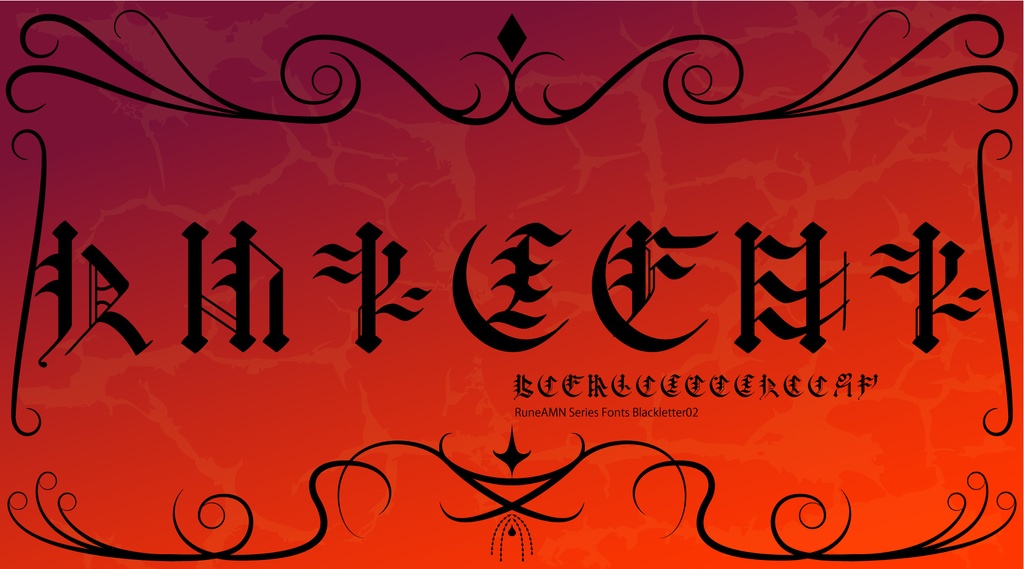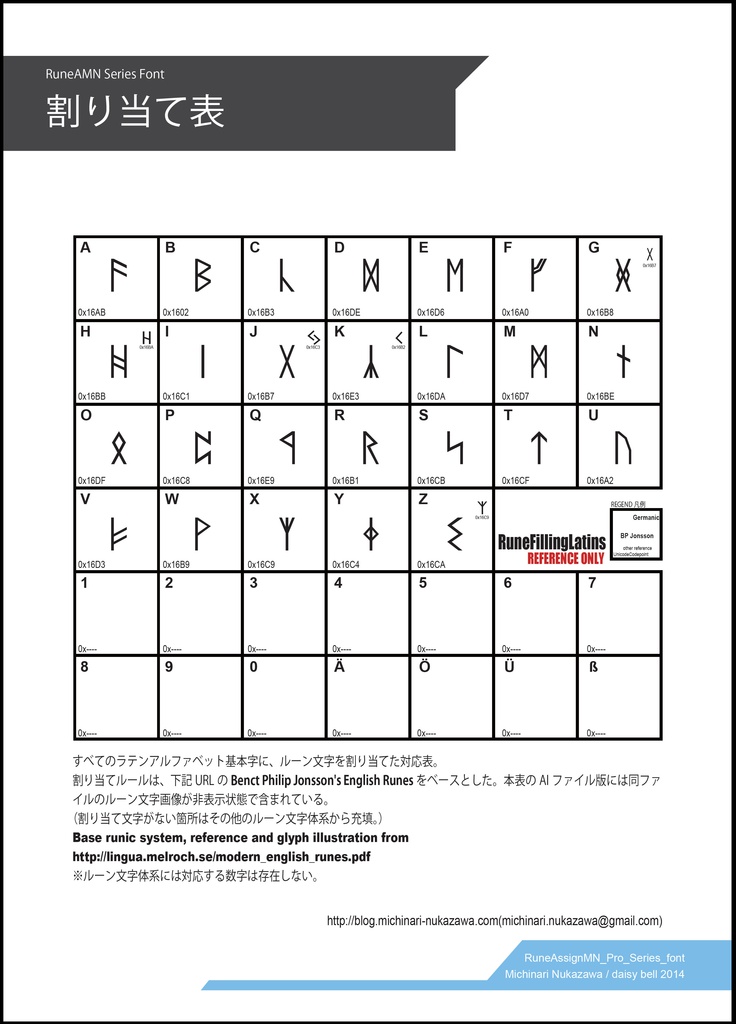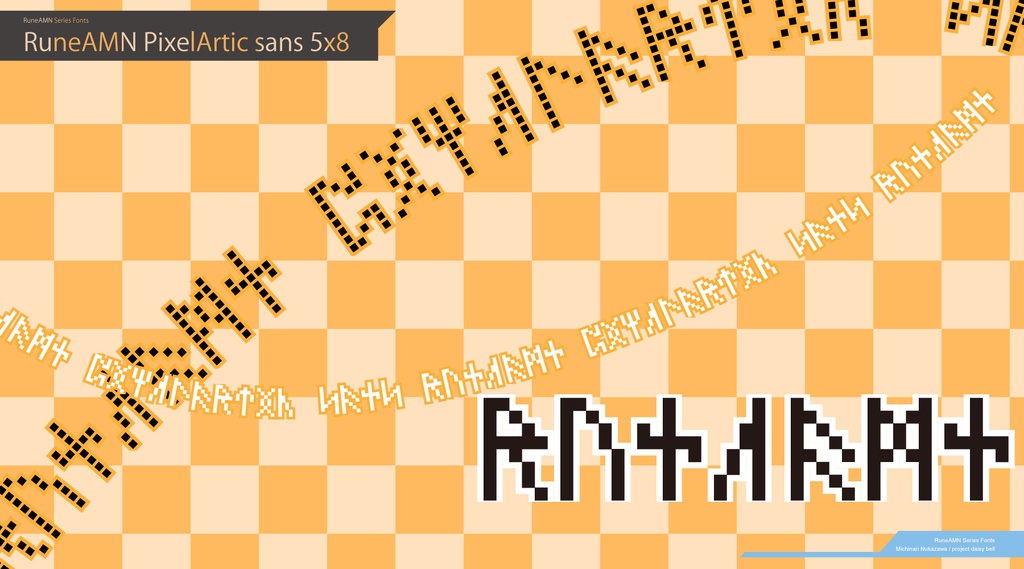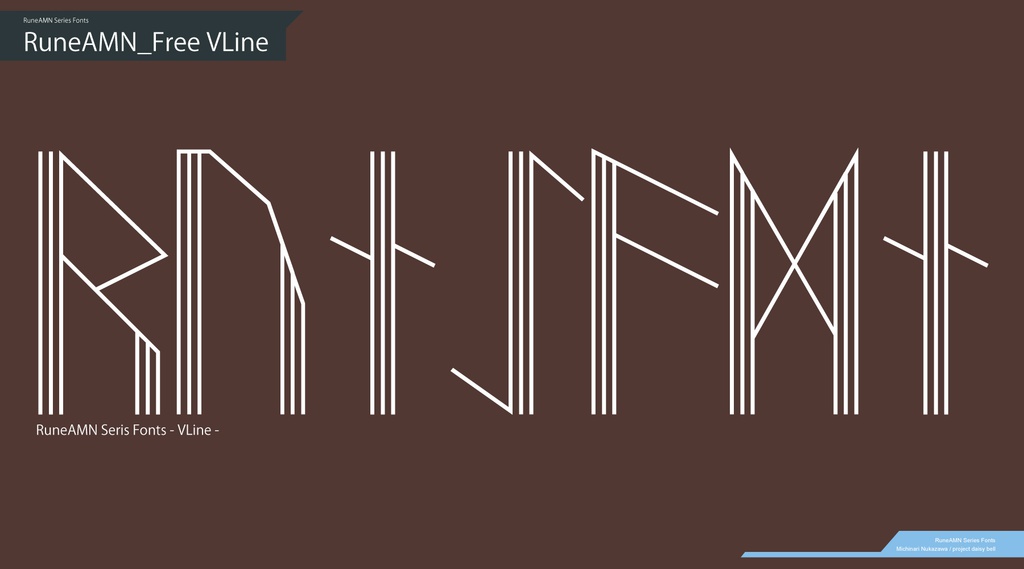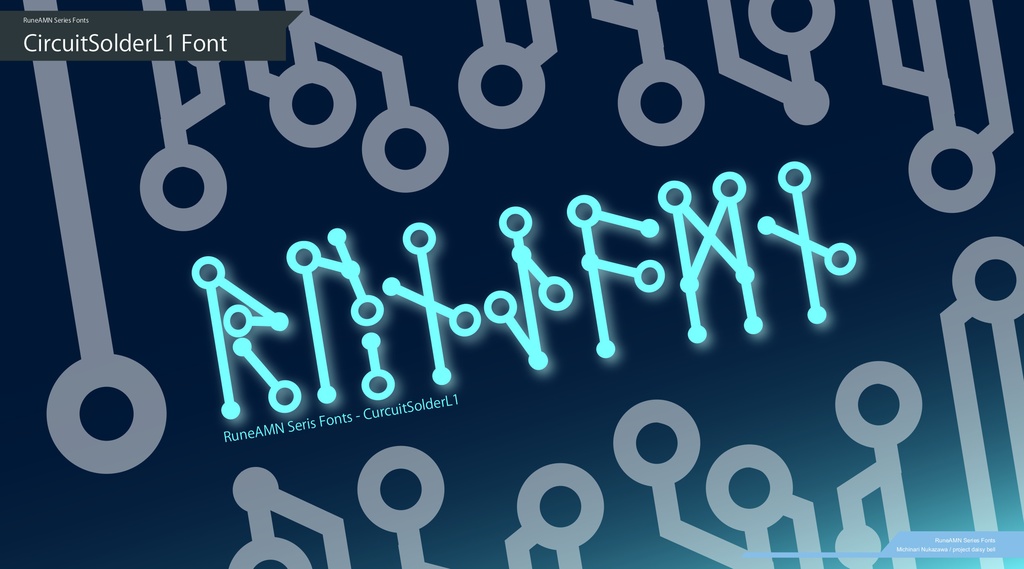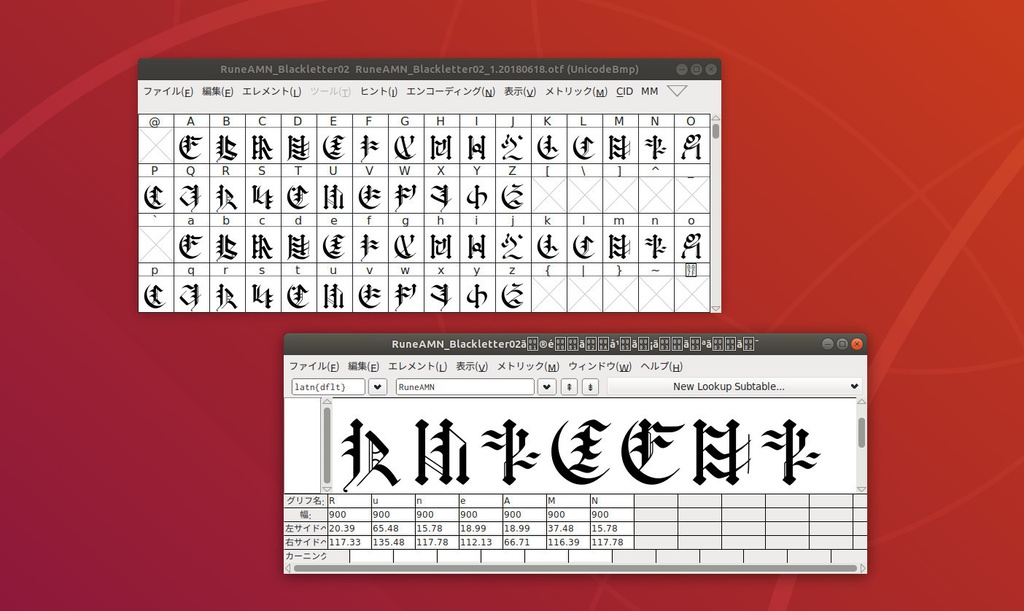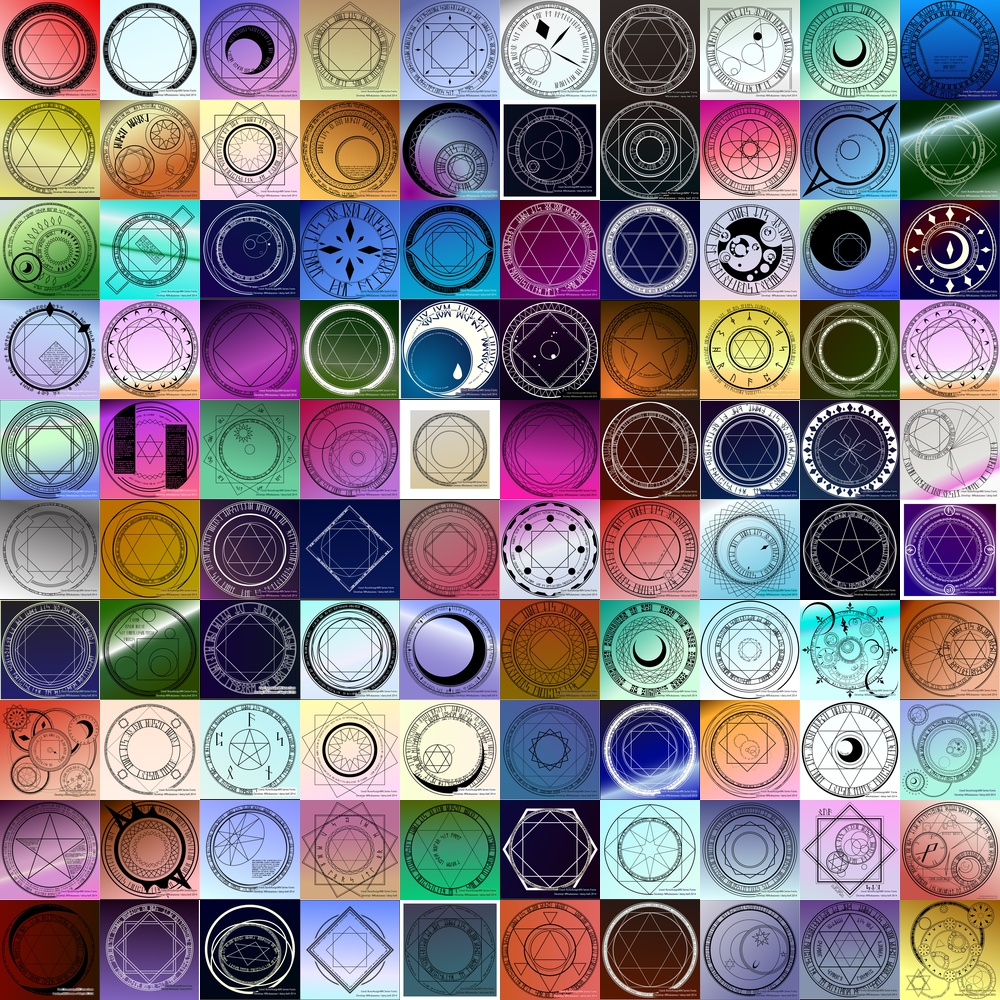
ルーン文字 フォントセット (商用版) RuneAMN_Pro Series
ルーン文字フォントのセットです。 イラスト・デザイン向けの装飾性の高い書体が揃っています。 『理由なしの90日間返品保証』付き。 購入済みユーザ様へ無償アップデートを提供しています。 最新版をダウンロードできます。 ※2015/07/07アップデートしました(新フォント追加ほか)。 ※2017/05/10アップデートしました(新フォント追加ほか)。 ※2018/01/16アップデートしました(新フォント追加)。 ※2018/12/31アップデートしました(新フォント追加) ※2018/06/19アップデートしました(新フォント追加)。 ※2020/09/27アップデートしました(新フォント追加)。 ※2021/01/17アップデートしました(新フォント追加)。 全書体見本(Webページ) http://michinarinukazawa.github.io/RuneAMN_Pro_Series_Fonts/docs/runeamn_pro.html 全書体見本(PDF版) https://github.com/MichinariNukazawa/RuneAMN_Pro_Series_Fonts/raw/gh-pages/releases/book_of_RuneAMN_Pro_Fonts_limited.pdf 『RuneAssignMNシリーズ』は、ルーン文字を一般的な環境で入力が簡単なラテン・アルファベット(A〜z)に割り当てたフォントです。 ファンタジーなイラスト・デザインなど。 BOOTHアカウントをお持ちでない場合、Gumroadでも購入可能です。 https://gumroad.com/l/UNWF 本製品のライセンスは下記URLのとおりです。 (イラスト・アート・立体物・漫画等) https://github.com/MichinariNukazawa/RuneAMN_Pro_Series_Fonts/blob/gh-pages/docs/etcs/LICENSE.txt (ゲーム・アプリ開発などで)多人数での開発やライセンスに含まれない利用方法をご希望の場合は、個別許諾やディスカウントライセンス等ご相談をお受けいたします。 別途お問い合わせください。 サポートはメールまたはtwitterにて行っています。 ご意見・ご要望も気軽にお寄せください。 mail: michinari.nukazawa@gmail.com twitter: https://twitter.com/MNukazawa